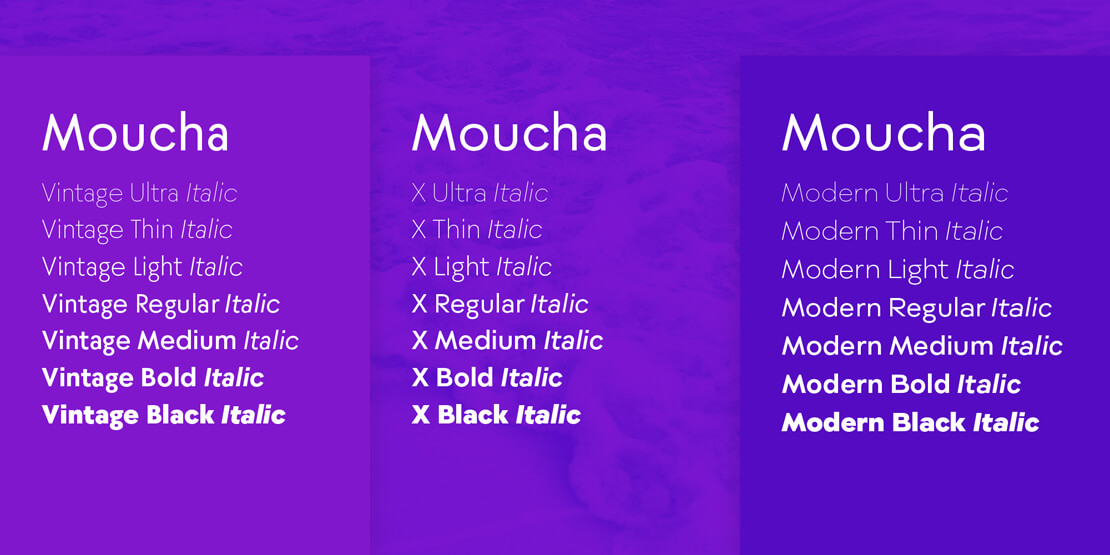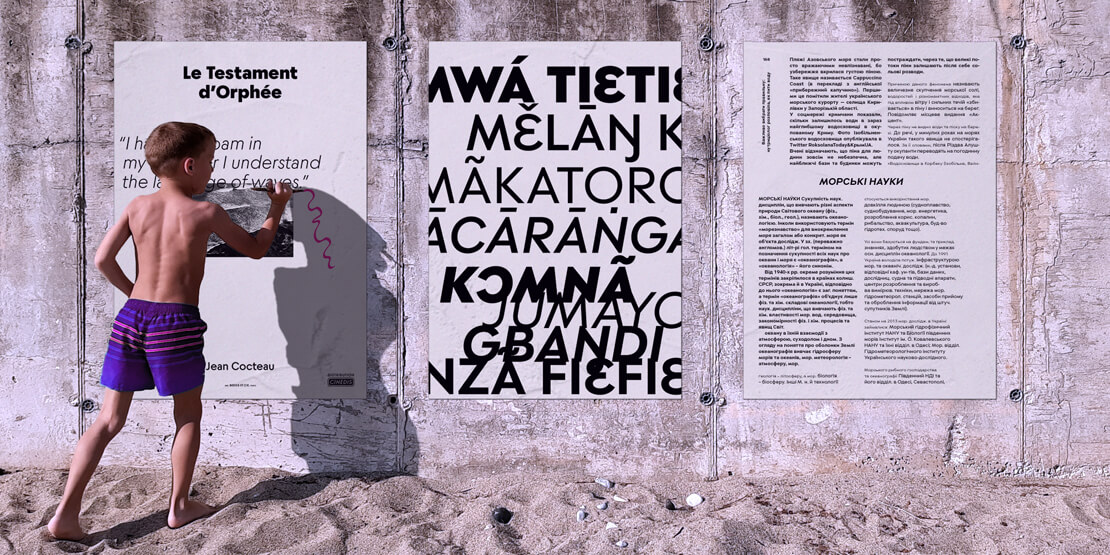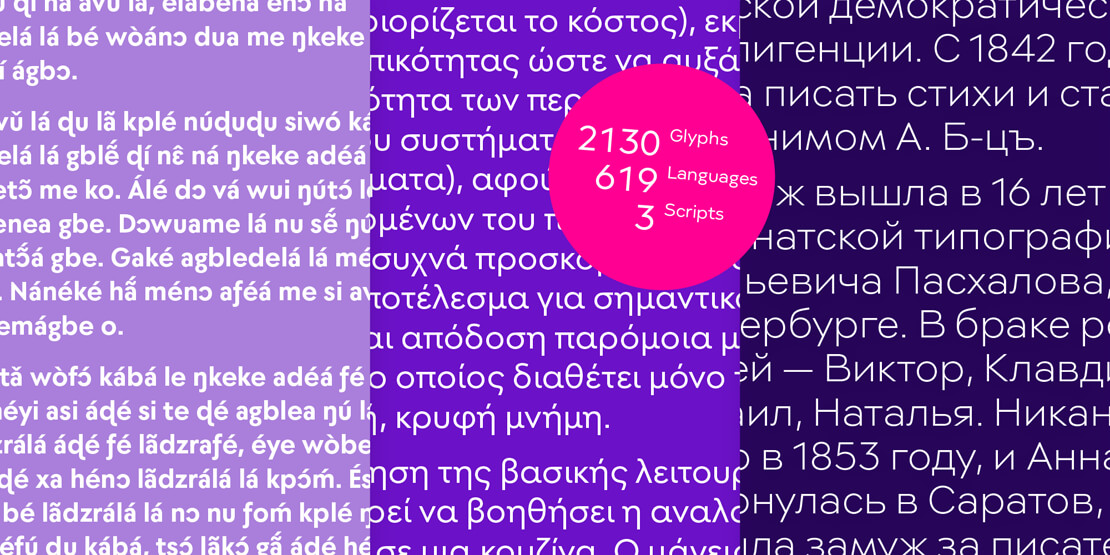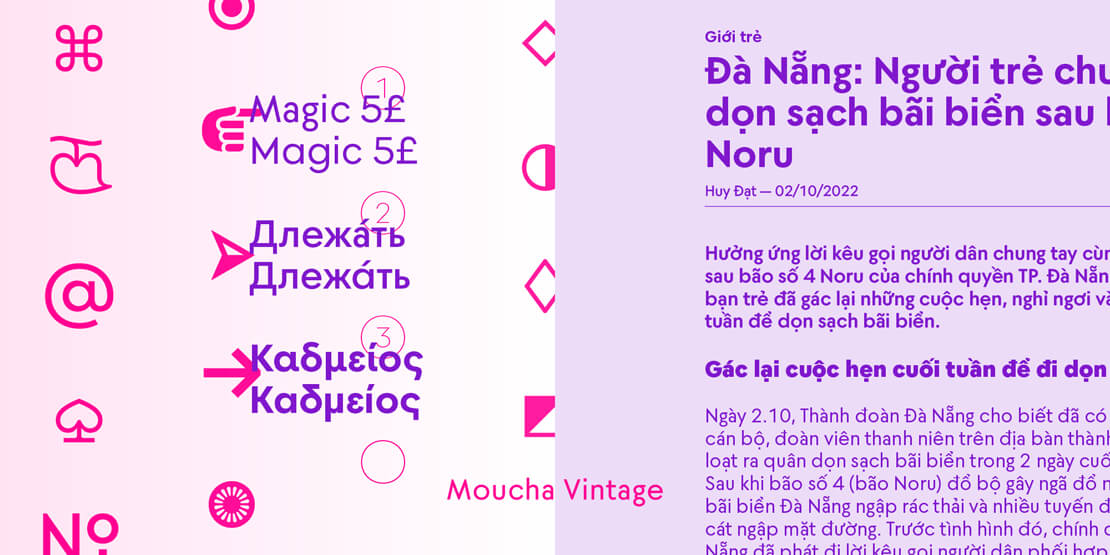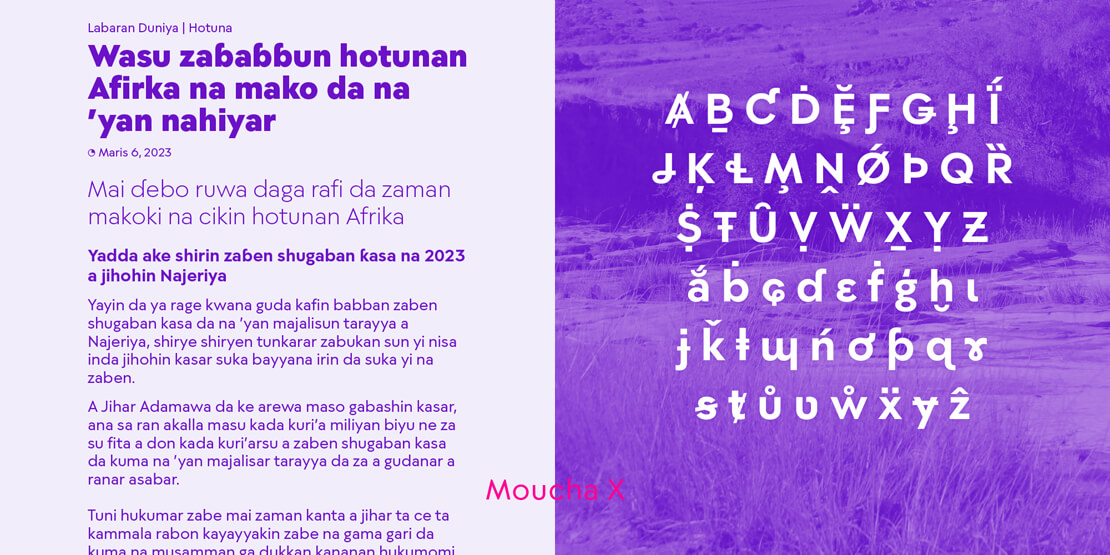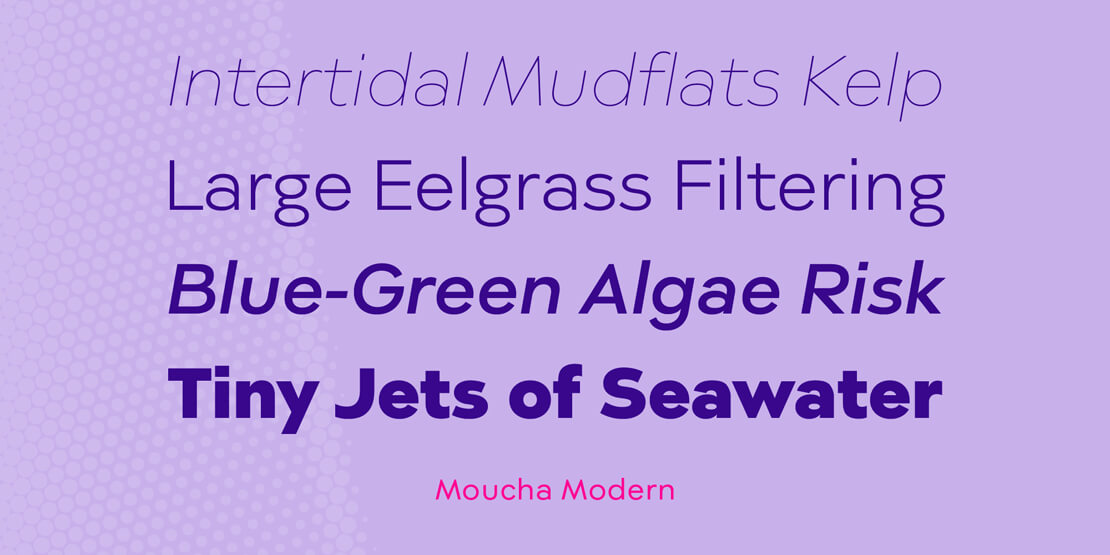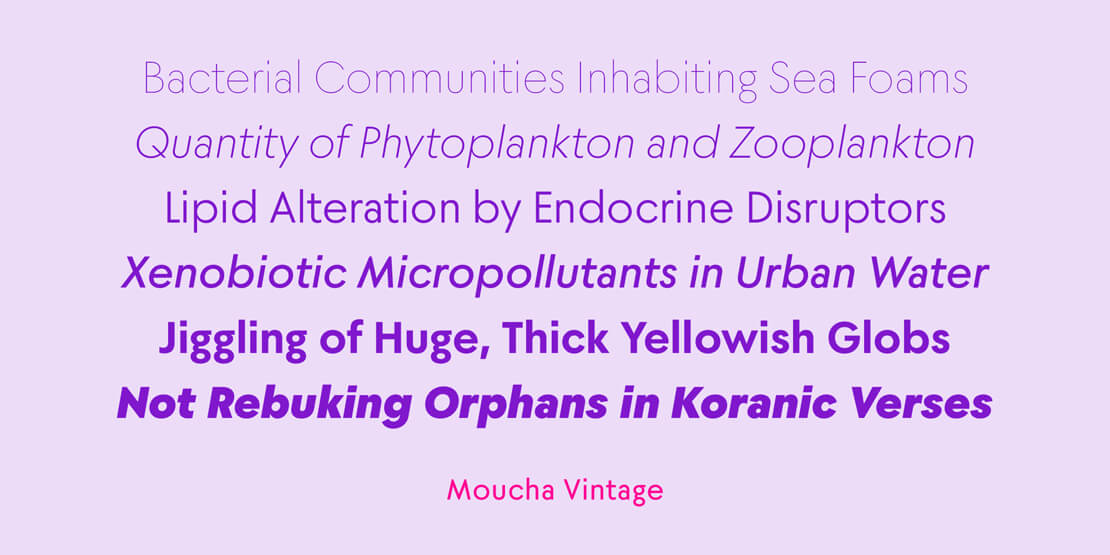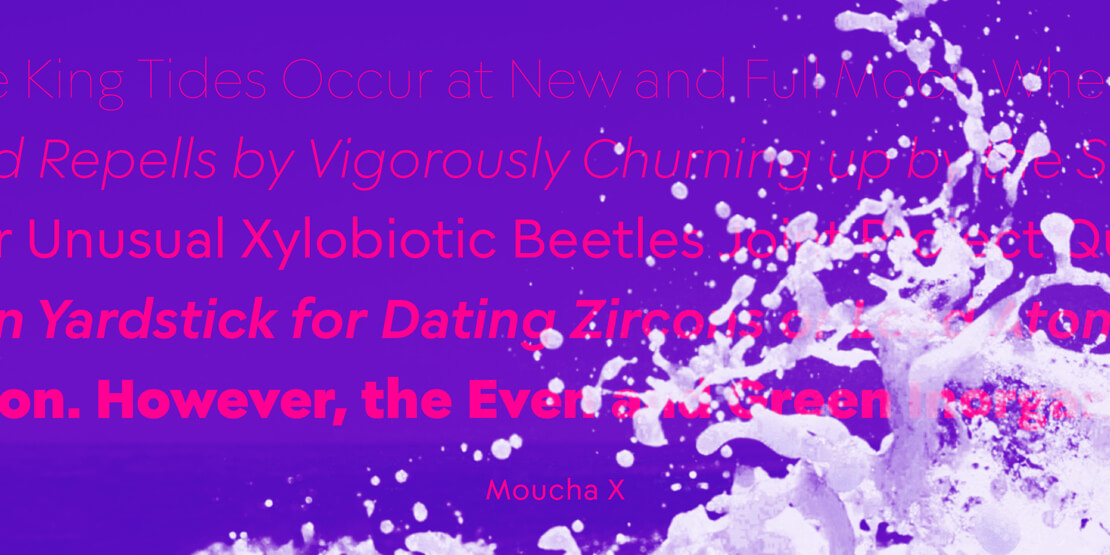
Das variable System von »Moucha«
Lieber klassisch oder doch eher homogen und zeitgenössisch? Die neue Multi-Subgenre-Superfamilie »Moucha« von Philip Lammert ist da und enthält über 2.100 Glyphen. Neben den 42 statischen Fonts haben alle drei Schriftfamilien ihre eigenen aufrechten und kursiven Variable-Fonts.
Moucha ist eine neue Schriftart, die von Philip Lammert entworfen und unter seinem Foundry-Namen Vibrant Types veröffentlicht wurde – eine Superfamilie von serifenlosen Schriftarten, die die Untergruppen des geometrischen Genres abdeckt.
Sie besteht aus den beiden Schriftfamilien »Moucha Vintage« und »Moucha Modern«, die den klassischen und modernen Look repräsentieren. Während der Variable-Font alle Zwischenvarianten verfügbar macht, markiert »Moucha X« die genaue Mitte.
Das System »Moucha«
Alle Schriftfamilien-Varianten haben dieselben runden Zeichen (wie „o“, „b“ oder „d“), während sich die auf Rechteckten basierenden Zeichen (wie „n“, „h“ oder „u“) in der Breite unterscheiden. »Moucha Vintage« bietet einen rhythmischen, klassischen Look mit einem schmalen „n“ und Großbuchstaben-Proportionen, wie von Genre-Prototypen (z.B. Futura) bekannt. »Moucha Modern« steht für ein homogenes, statisches Erscheinungsbild mit der ausgeglichenen Zeichenbreite des zeitgenössischen Subgenres, während »Moucha X« den Mittelpunkt zwischen den extremen Polen repräsentiert.
Neben den 42 statischen Fonts haben alle drei Schriftfamilien ihre eigenen aufrechten und kursiven Variable-Fonts für einen besseren Fokus bei der Designarbeit. Die übergeordnete Superfamilie »Moucha« verfügt über zwei Variable-Fonts, die alle Zwischenstufen zwischen den beiden Extremen möglich machen.
Die Fonts bieten alternative Formatvarianten, darunter ein Stylistic Set mit noch statischeren Zeichen, ein offeneres Modern „a“, ein „l“ mit kursivem Strichende, ein weniger reduziertes „u“ und eine durchgestrichene Null. Weitere Font-Features sind unter anderem Pfeile, zusätzliche Ziffernsätze und Versalformen.